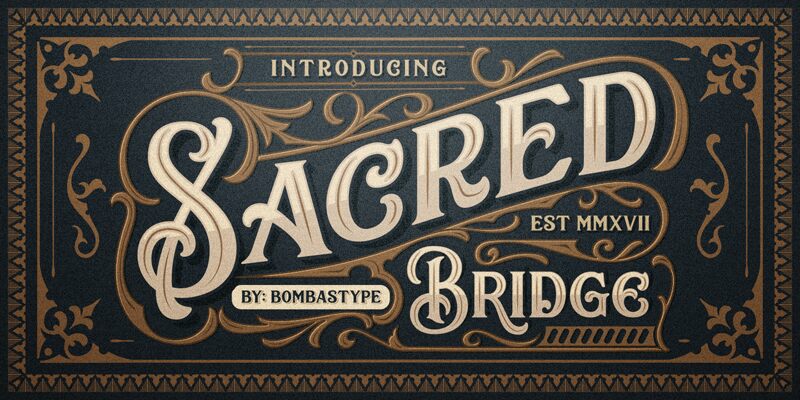
Sacred Bridge, entworfen vom Designhaus Bombastype, ist ein eindrucksvolles Beispiel für die zeitlose Anziehungskraft retro-inspirierter Display-Schriften. Mit seinen unverwechselbaren Zeichenformen und Verzierungen strahlt dieser Font eine Mischung aus klassischem Charme und moderner Raffinesse aus. Die harmonischen Kurven und kräftigen Striche erzeugen einen wirkungsvollen visuellen Rhythmus, der den Betrachter sofort in den Bann zieht – eine exzellente Wahl für Branding, Verpackungsdesign und Überschriften.
Der einzigartige Reiz von Sacred Bridge liegt in der Fähigkeit, das Publikum in vergangene Zeiten zu entführen und dabei eine klare, zeitgemäße Ästhetik zu bewahren, die perfekt zu modernen Designs passt. Die Vielseitigkeit zeigt sich in verschiedensten kreativen Projekten – von redaktionellen Layouts, die einen Hauch von Nostalgie verlangen, bis hin zu Postern, die mit Vintage-Flair Aufmerksamkeit erregen. Sacred Bridge schlägt die Brücke zwischen historischer Inspiration und gegenwärtigem Designempfinden.